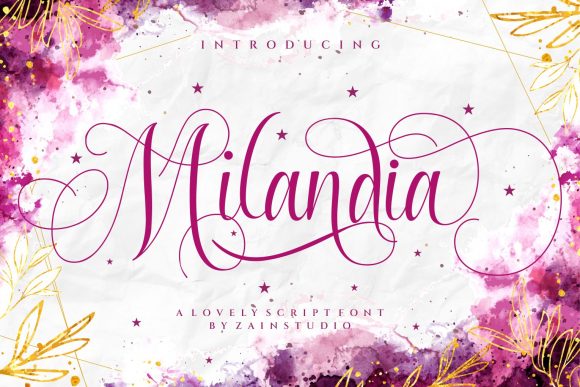
Creativefabrica Milandia Font 2021
[Creativefabrica] Milandia Font (2021)
Миландия - это красивый легкий рукописный шрифт с уникальными ощущениями и потрясающим эффектом.
Он добавит роскошной искры в любой дизайн-проект, который вы хотите создать!